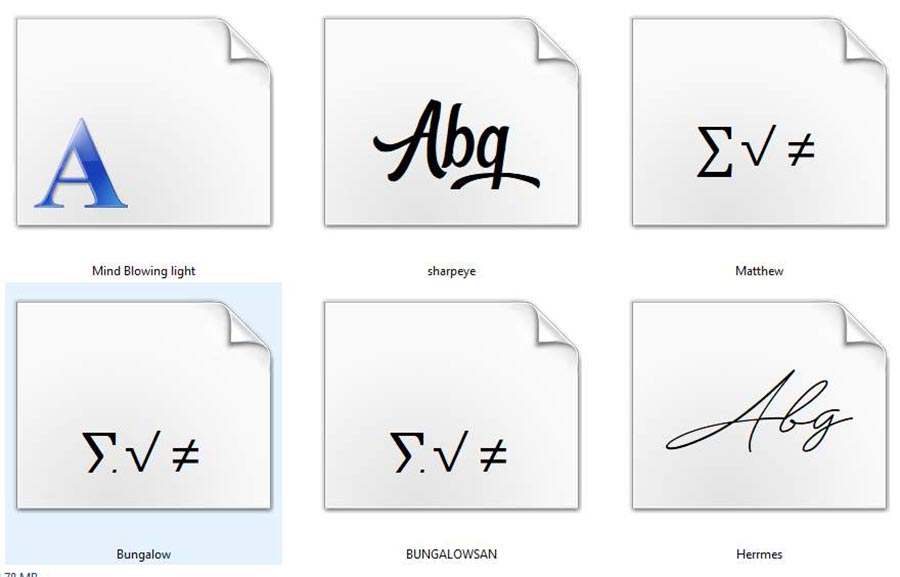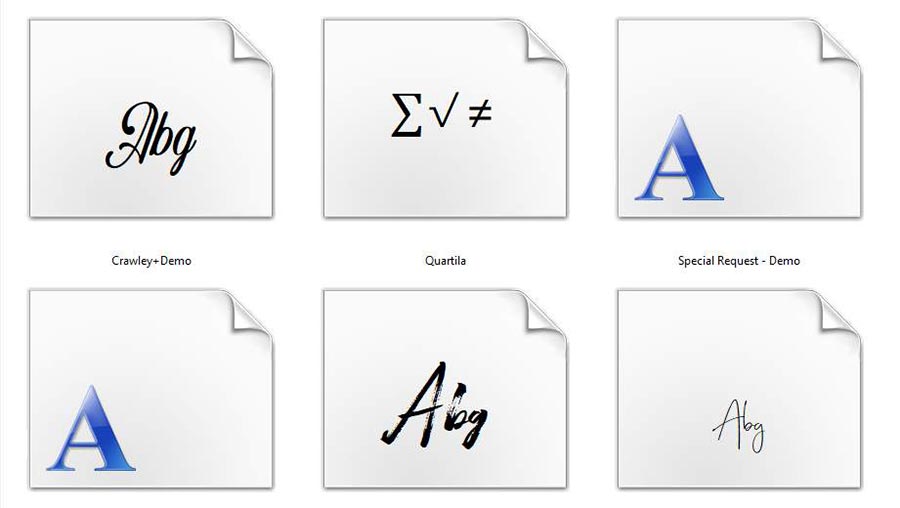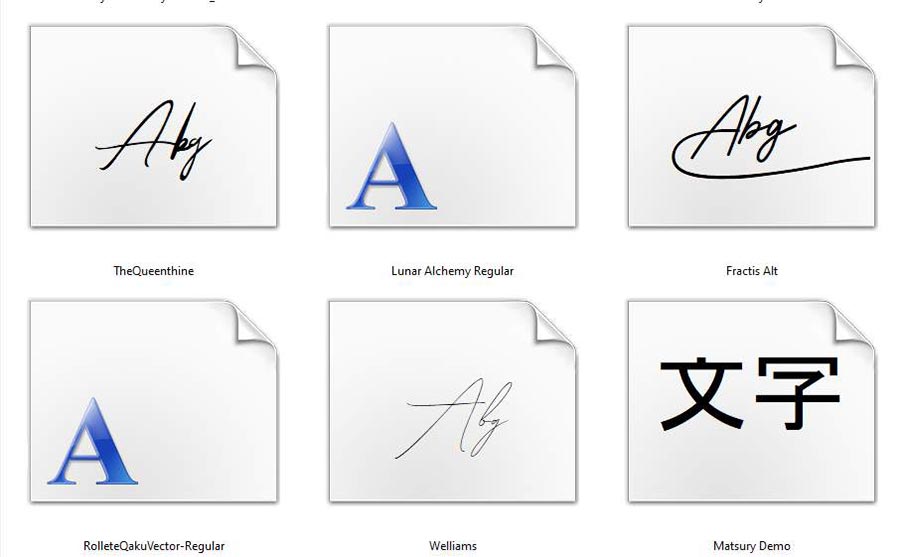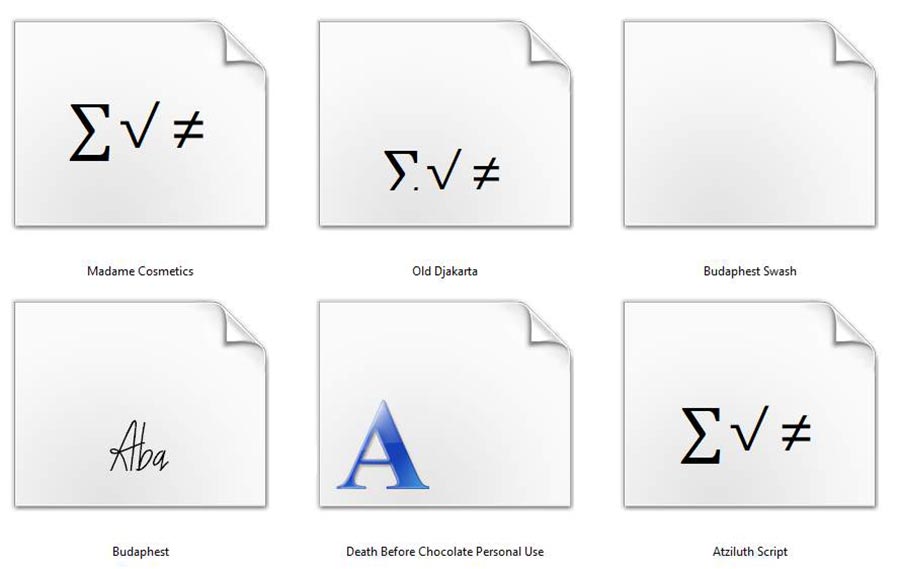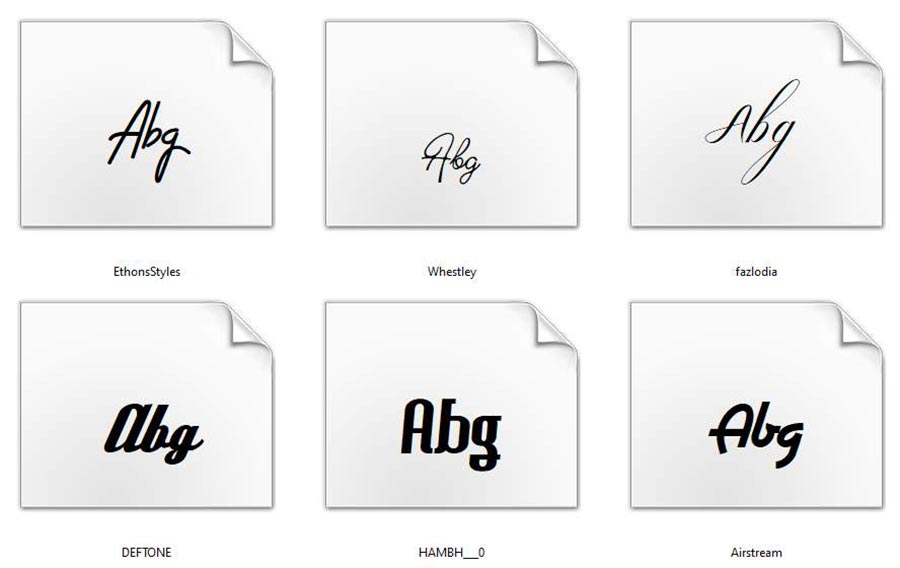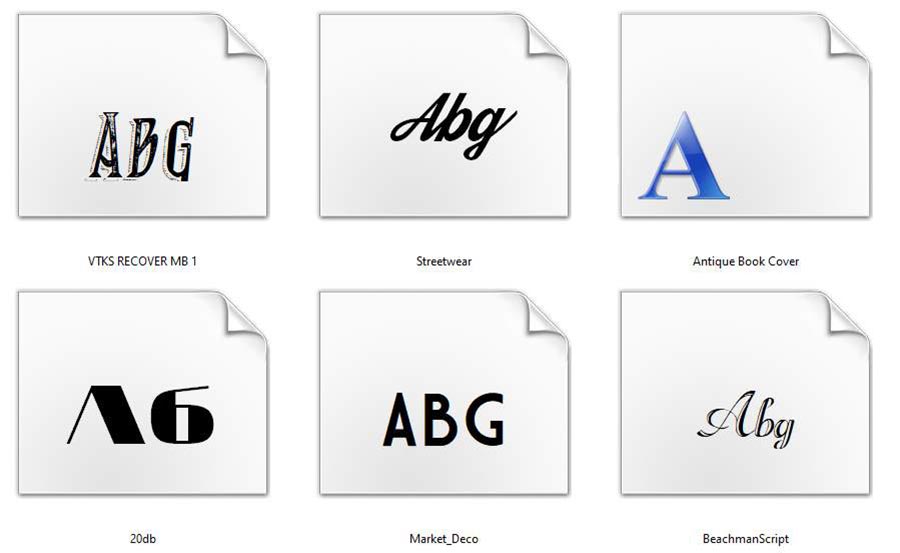
Bộ Font Chữ Xưa Cũ - công cụ hoàn hảo cho những ai yêu thích phong cách hoài cổ, mang đậm dấu ấn thời gian. Với thiết kế gợi nhớ đến các bảng hiệu, sách báo, hoặc tài liệu từ thế kỷ trước, những font chữ này sẽ thổi hồn cổ điển vào các tác phẩm sáng tạo của bạn. Tải ngay bộ font chữ xưa cũ miễn phí tại Sadesign.vn để mang phong cách hoài cổ vào các thiết kế của bạn. Đơn giản, nhanh chóng và đầy sáng tạo.
1. Giá trị của font chữ xưa cũ trong thiết kế
Font chữ xưa cũ thường được yêu thích nhờ khả năng gợi nhớ về những thời kỳ vàng son, với đường nét đậm chất cổ điển và tinh tế. Những lợi ích nổi bật của loại font này bao gồm:
• Tái hiện phong cách hoài niệm: Mang đến cảm giác cổ xưa, phù hợp với các thiết kế lấy cảm hứng từ lịch sử hoặc vintage.
• Nâng cao tính sáng tạo: Kết hợp hài hòa giữa các yếu tố truyền thống và hiện đại.
• Tăng tính nhận diện thương hiệu: Thích hợp cho những thương hiệu hướng đến giá trị bền vững và di sản văn hóa.
2. Bộ font chữ xưa cũ tại Sadesign.vn có gì đặc biệt?
Sadesign.vn đã sàng lọc và cung cấp miễn phí bộ font chữ xưa cũ chất lượng cao, phù hợp với nhiều dự án sáng tạo. Điểm đặc biệt của bộ font này bao gồm:
• Thiết kế độc đáo: Các chi tiết được chăm chút kỹ lưỡng, mang đậm dấu ấn thời gian.